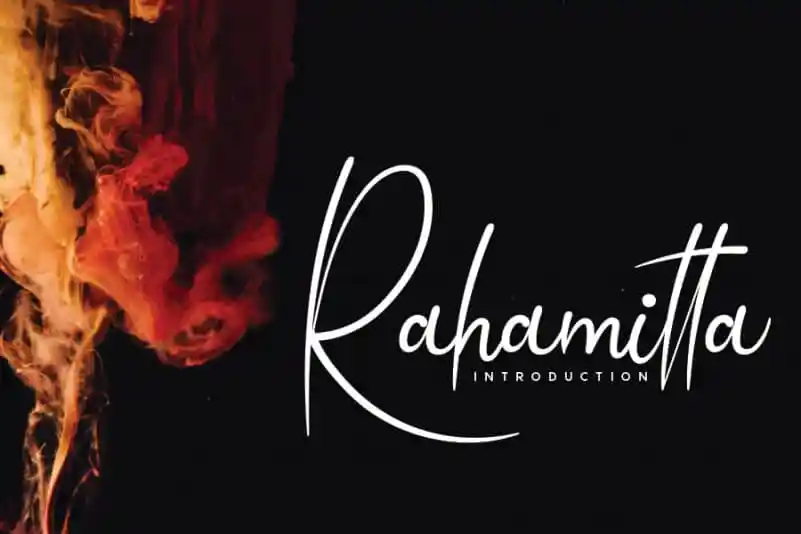
Rahamitta Handwritten Font – Download Grátis
A Rahamitta Handwritten Font é uma escolha perfeita para quem valoriza detalhes delicados e elegância na tipografia. Esta fonte manuscrita flui naturalmente, com belos caracteres bem equilibrados que permitem uma harmonia perfeita em qualquer projeto design. Suas linhas suaves e harmoniosas criam um estilo único que se adapta a uma ampla variedade de ideias criativas. Experimentar a Rahamitta é como dar vida às suas concepções mais audaciosas e visionárias, tornando-as realidade através da palavra escrita. Se você procura algo para enriquecer seus projetos design com elegância natural e profundidade de detalhe, esta fonte será uma ótima escolha.